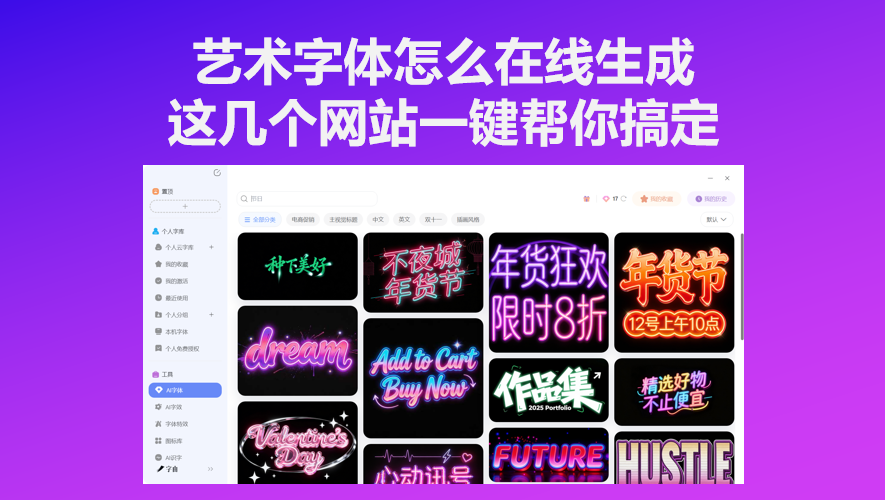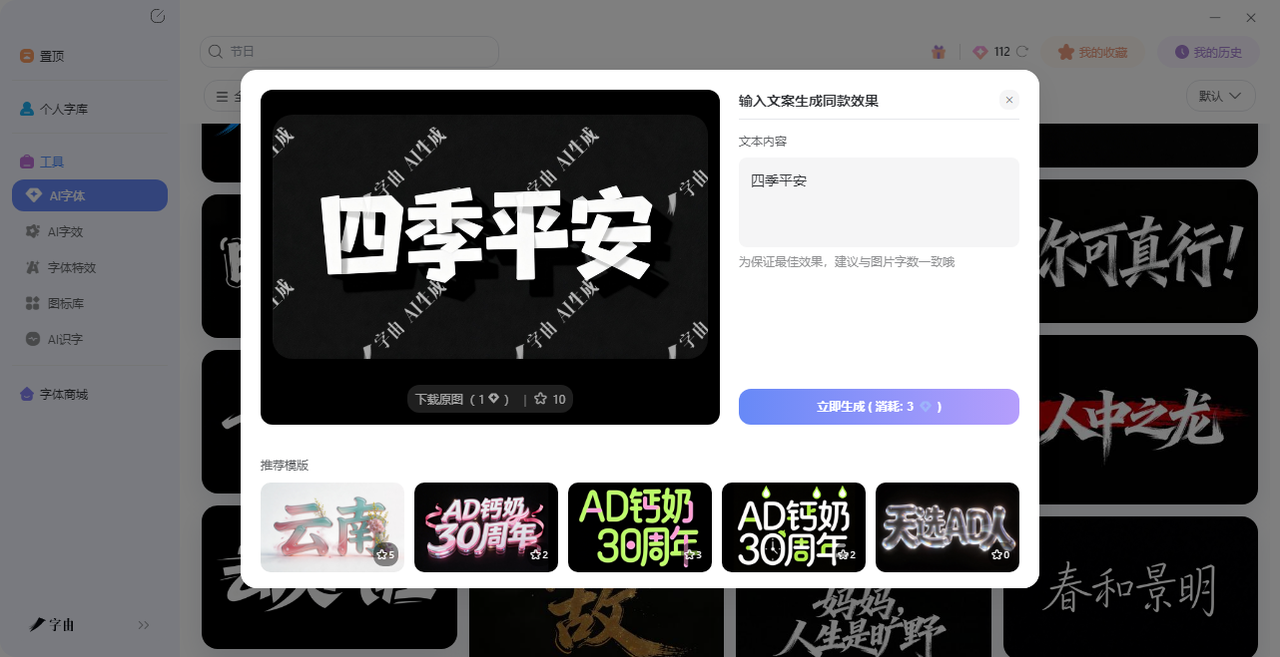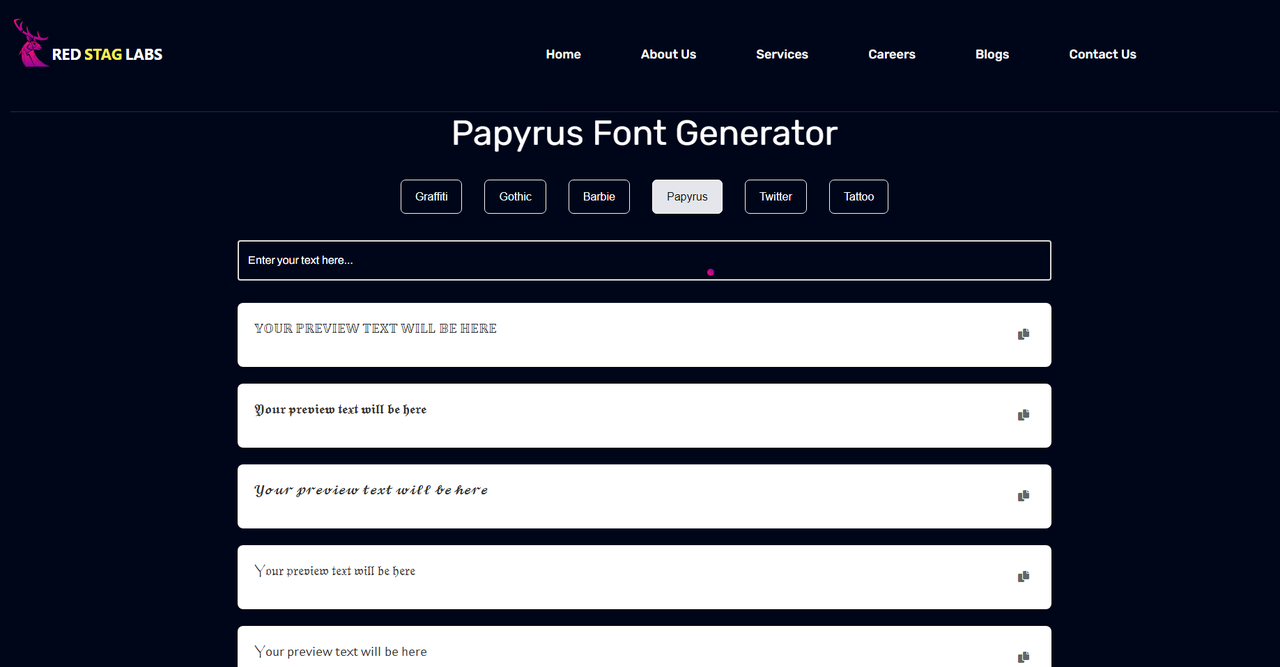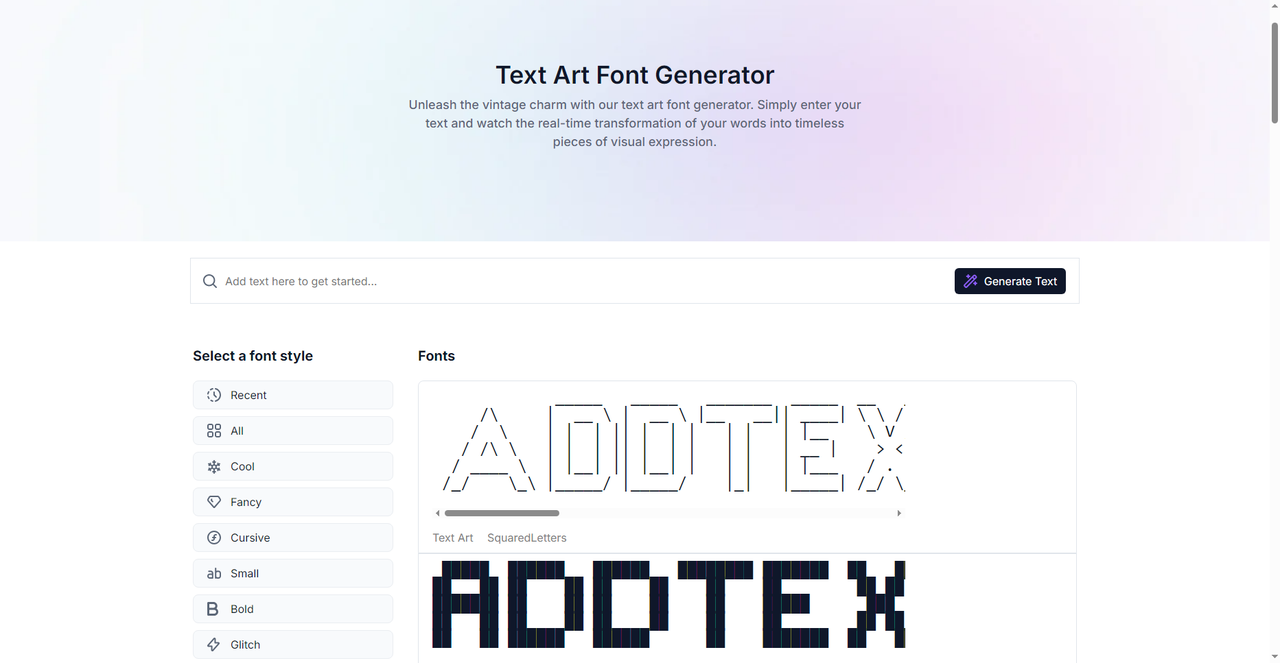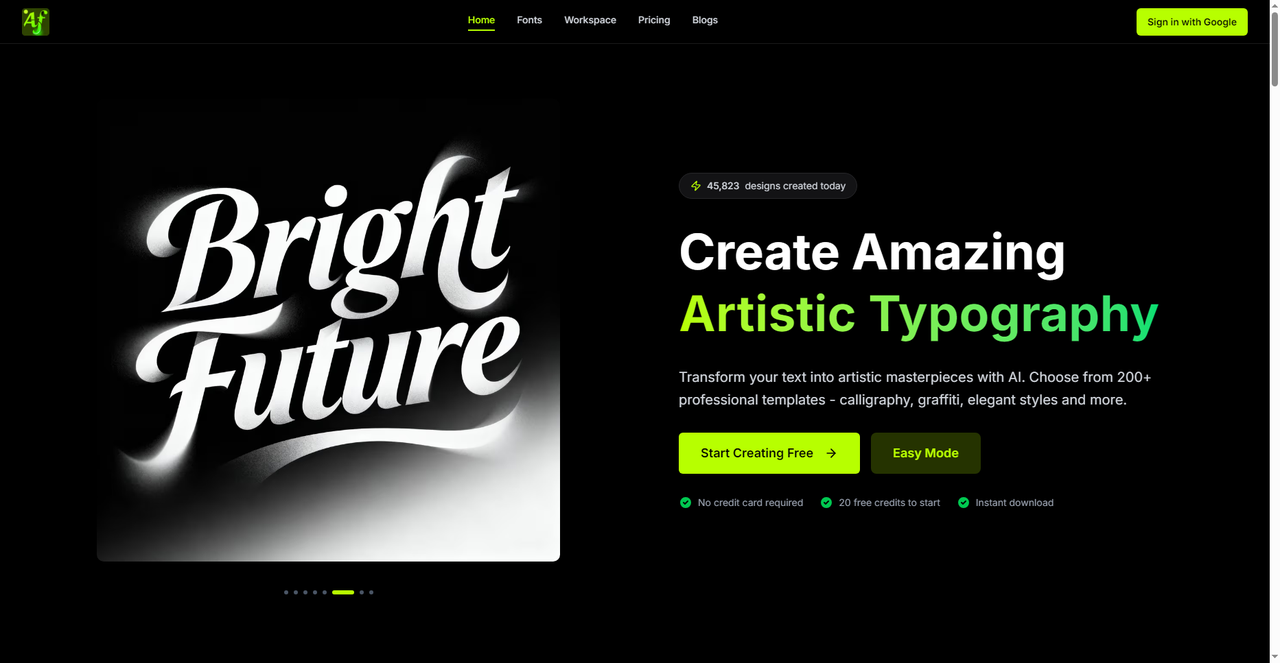
艺术字体怎么在线生成?这几个网站一键帮你搞定
做海报标题、发社交媒体配图、做 Logo 的时候,你是不是也遇到过这种情况:想在封面上放一行醒目的标题,但电脑自带的字体不是太普通就是太死板。打开 PS 也没什么设计思路。其实现在有很多艺术字体在线生成工具,输入文字选个模板就能出图。今天整理了 5 个免费好用的在线工具,覆盖了不同的使用场景。输入名字,点一下生成,几秒就能下载到一张能直接用的艺术字图。感兴趣的话可以来看看我下面的介绍。
字由的 AI 字体就在客户端顶部“AI 工具”入口里。打开后你会看到一个模板库,具体操作流程非常简单:先根据场景筛选模板,比如要做一张国潮风海报,就在“风格”里选“国潮风”;找到喜欢的模板后点“做同款”,在右侧文本框里把模板里的文字换成你自己的文案;点“立即生成”,等待 10 到 15 秒,系统就会生成一张带有特效的艺术字图片。
字由 AI 字体的另一大优势是模板质量高。字由与汉仪字库、蒙纳字库等多家顶尖字库公司深度合作,模板调用的都是经过专业打磨的正版字体,不是随便拼凑的效果。生成后的文字笔画规整、没有错字,也不会出现字体扭曲或者间距混乱的问题。依托字由平台的正版字体库,生成的 Logo、海报标题等文字设计可商用,能提供授权证明。对于那些完全不懂排版和字体设计的新手来说,字由 AI 字体基本是零门槛——选个模板,改几个字,10 秒出一张图。
2、Papyrus Font Generator
第二个工具来自 Red Stag Labs 的 Papyrus Font Generator。Papyrus 是一款经典的装饰性字体,灵感来自古埃及的莎草纸,笔画边缘带着手绘的不规则质感,有一种天然的古朴感。这款字体在电影《阿凡达》的海报中用过之后更出名了,至今仍是最具辨识度的装饰字体之一。Papyrus Font Generator 的使用方式很简单:在输入框里输入你的文字,它会自动转换成 Papyrus 字体风格的预览效果。如果你做的是复古风格的海报、埃及主题的活动物料、或者想要一种“手写在莎草纸上”的自然质感,这款生成器可以直接帮你预览效果。它特别适合制作邀请函、名言警句、创意标题等场景。
对于喜欢复古、波西米亚、埃及风格的设计师来说,Papyrus 字体生成的标题非常有氛围感。不过需要注意的是,Papyrus 字体主要用于英文和拉丁字母的展示,中文字体场景不适用。如果你做的是纯英文项目,或者中英文混排中英文部分需要突出的标题,Papyrus Font Generator 是个不错的备选。
3、Fonts Generator
第三个工具是 Fonts Generator。这是一个功能很全的在线字体生成器,主打“Text Art”(文字艺术)风格,把文字转换成带复古感、像素风、艺术字效果的视觉作品。Fonts Generator 提供了 150 多种字体风格分类,包括复古、涂鸦、哥特、花体、粗体、小型大写、闪烁体等多种类型。它的“Text Art”系列是其最大的亮点——包含 SquaredLetters(方块字母)、Retovibes(复古氛围)等多种艺术字风格,很适合用在社交媒体配图、短视频标题、个人网站 Banner 等场景。
操作方式也很直接:在输入框里打字,右侧会实时显示不同字体风格下的预览效果,点击喜欢的风格就能复制或下载。如果你需要的是那种“有点不一样、有点艺术感”的标题字,Fonts Generator 的 Text Art 系列值得一试。
4、Font Generator
虽然名字相同,和上一个不是同一个网站。这一款的特色是提供了 170 多种字体和 10 种字体风格(包括花体、草书、小型大写、闪烁体、数学符号体等),用户评分高达 4.8 分(1284 条评价)。它的界面非常简洁:中间一个大输入框,输入文字后,下面会列出所有可用的字体样式,每种样式都有对应的预览文字,点一下就能复制转换后的文本。与其他生成器不同,这个工具不生成图片,而是直接输出 Unicode 特殊字符格式的文本——这意味着你可以把生成的花体字直接复制粘贴到 Instagram、Twitter、TikTok、微信朋友圈等任何支持 Unicode 的平台上,不需要下载图片再上传。
这种“复制即用”的模式非常适合社交媒体内容创作者。如果你想在评论区或帖子标题里用花体字、哥特体、闪烁体来吸引眼球,这个 Font Generator 是最方便的。而且它完全免费,不需要注册。
5、ArtFont
第五个工具是 ArtFont。这是一款 AI 驱动的艺术字体生成平台,官方宣称拥有 200 多种专业模板,覆盖书法、涂鸦、优雅、可爱等多种风格。ArtFont 的亮点在于它的 AI 生成质量:支持 2K 标准画质和 4K 可选画质,生成的 PNG 和 JPG 图片可以直接用于印刷或网页。它还提供实时预览功能,输入文字后可以实时看到 AI 生成的效果。ArtFont 还有一个社区功能,可以浏览其他用户创作的 120 万多种字体效果,从中寻找设计灵感。
ArtFont 的核心逻辑和字由类似——选模板、输文字、出图。它的模板数量是 200 多种,比字由的 400 多种少一些,但在高清画质和 AI 生成速度上表现不错。如果你需要生成高质量的印刷级艺术字,ArtFont 是一个值得尝试的备选。需要说明的是,ArtFont 在中文模板的支持上可能不如字由丰富,更适合英文项目。
最后,我想说,如果你经常用中文的话,字由是最好的选择,多种 AI 字体模板覆盖电商促销、新媒体封面、国潮风等多种风格。10 秒生成可商用的艺术字图这几个工具基本都是免费的,挨个试一遍,总能找到适合你项目的那一款。以后再也不用为艺术字体在线生成这件事发愁了。